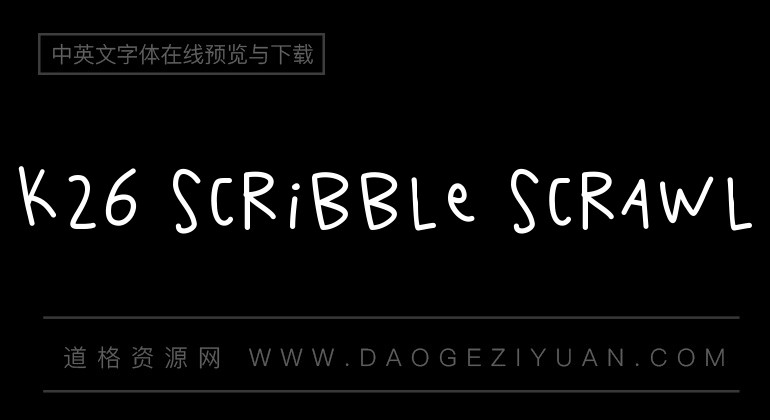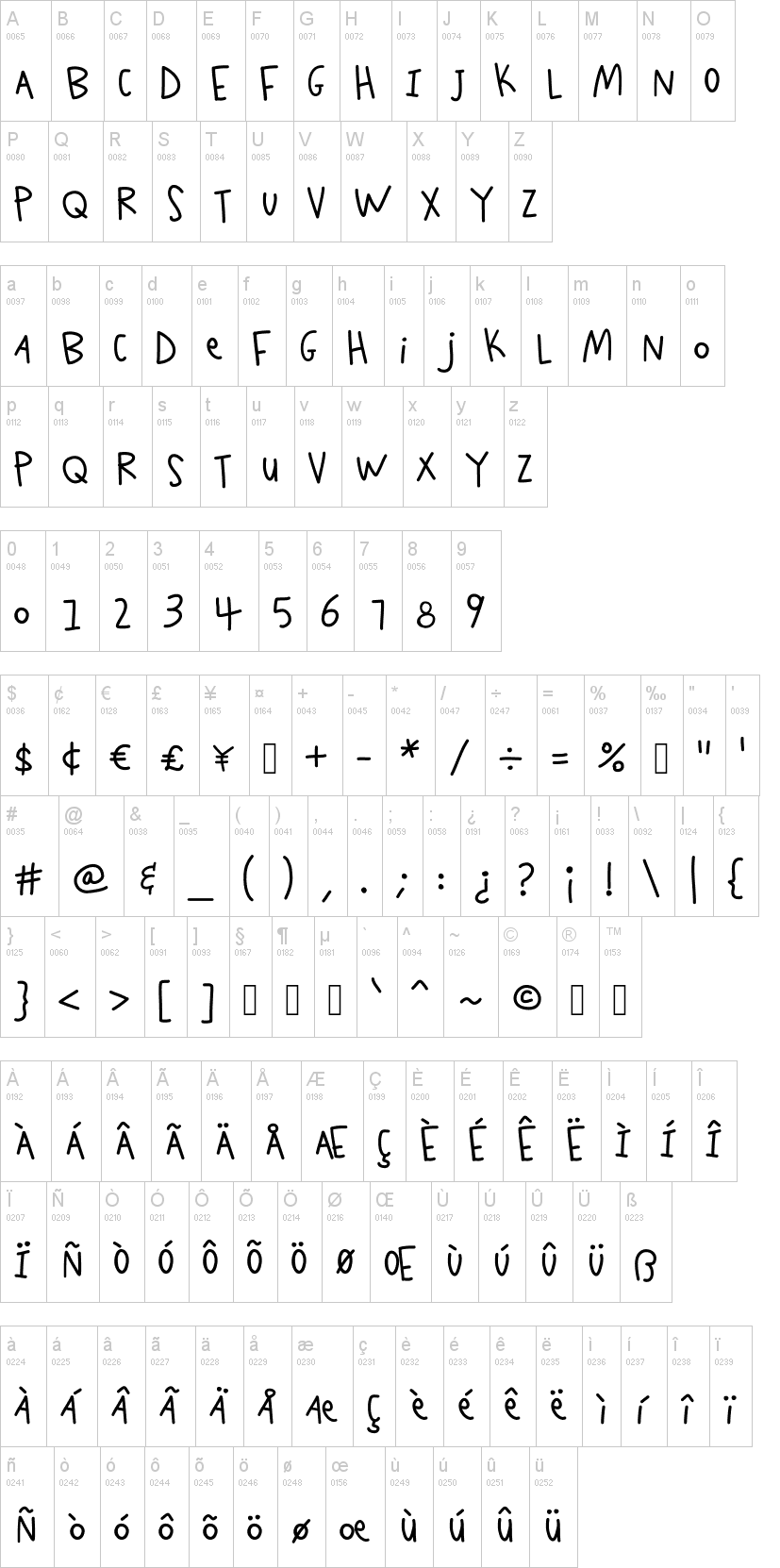
K26 Scribble Scrawl是一种手写风格的字体,具有非常独特的风格和视觉效果。这种字体适用于设计师、艺术家和插画家等创意人群使用,可以用于设计海报、标志、宣传册、广告等各种创意作品。 K26 Scribble Scrawl 字体的特点是具有非常明显的手写风格,字母较为简单,线条粗细不一,各个字母之间的距离也不规则,让人感觉非常自然、随意。这样的视觉效果使得该字体具有非常强的艺术感和创意感,可以将文字与画面非常好地融合在一起,达到更好的视觉效果。 此外,K26 Scribble Scrawl 字体还具有多种不同的字重和字形,可以满足不同创意需求的设计师们的需求。该字体有多种格式,可以在各种设计软件中使用,如Adobe Photoshop、Adobe Illustrator等。 总之,K26 Scribble Scrawl 字体是一种非常独特的手写字体,具有艺术感和创意感,非常适合用于设计各种创意性的作品。内容介绍
K26 Scribble Scrawl是一款非常不错的手写艺术字体,具有很好的视觉感,适合于文化类的宣传设计、商业类品牌的广告和产品包装设计以及个性化文字排版等较多场景。